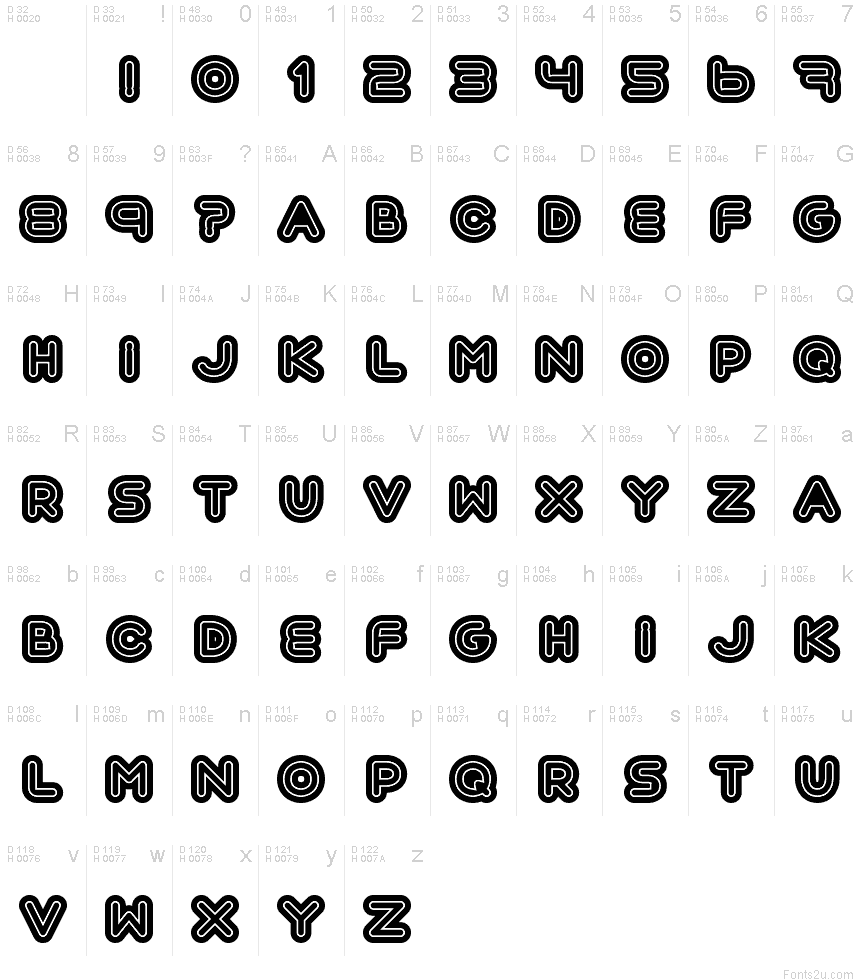
Automania od Fenotype to bezpłatny krój display w stylu retro, o grubych, tubowych obrysach, które przypominają neon wygięty w gładkie, pętelkowe litery. Podwójne linie tworzą odważny, świetlisty korytarz wewnątrz każdego znaku, nadając nagłówkom dynamiki i chromowanej nostalgii – w połowie jak z automatu do gier, w połowie jak emblemat zabytkowego samochodu. Duże, zaokrąglone formy sprawiają, że krój jest przyjazny i czytelny nawet z dużej odległości.
Dzięki Automania stworzysz logo, plakaty, szyldy, okładki albumów, tytuły wydarzeń i wyraziste grafiki do mediów społecznościowych, które potrzebują zastrzyku retro energii. Ten bezpłatny font świetnie sprawdza się w dużych rozmiarach; połącz go z prostym, nowoczesnym bezszeryfowym krojem w tekstach uzupełniających, aby jego błyszczące, obrysowane kształty pozostały w centrum uwagi.